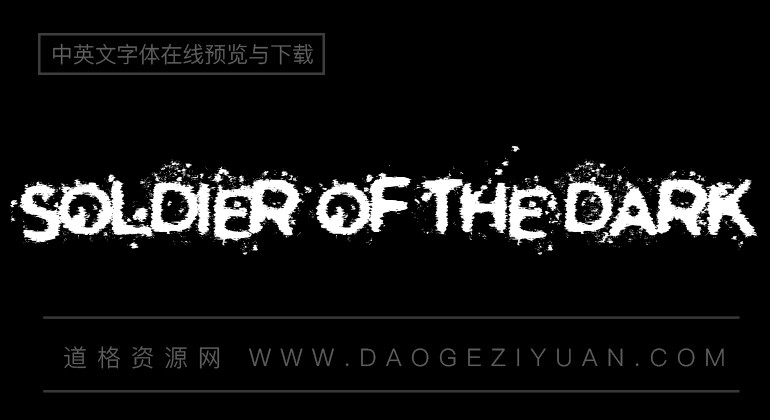
Soldier of the Dark
Soldier of the Dark 是一款由FontMesa出品的字体,它是一款深色的抢攻字体,带有暗示和暴力的感觉。它的字体设计具有深邃的内涵,能够为您的设计带来更多的想象力和灵感。它的字体设计特别适合用在海报、标志、T恤、书籍、网页、广告和其他设计中。
Soldier of the Dark是一款非常不错的手写艺术字体,具有很好的视觉感,适合于文化类的宣传设计、商业类品牌的广告和产品包装设计以及个性化文字排版等较多场景。